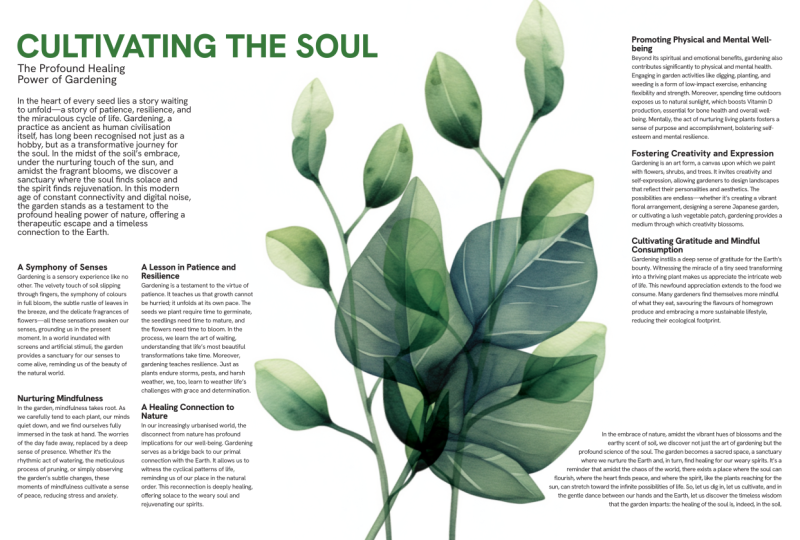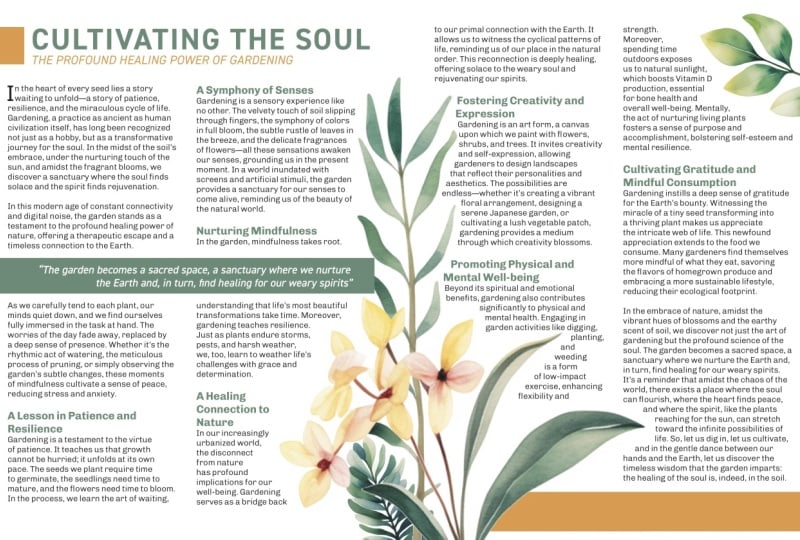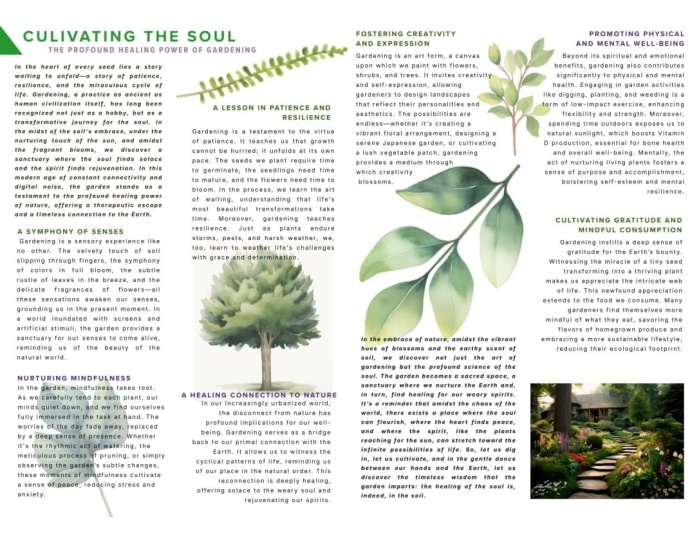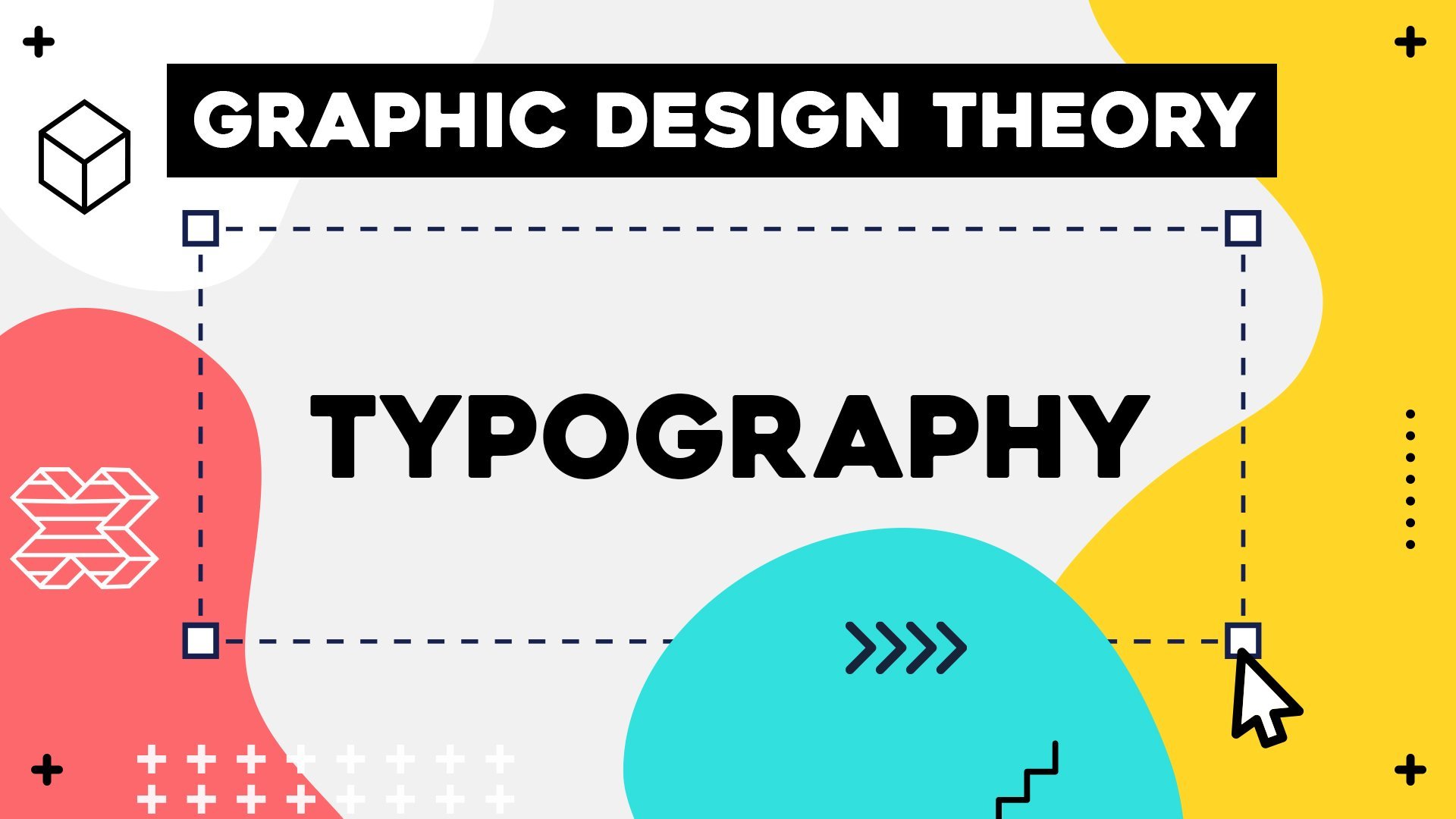
Theorie des Grafikdesigns – Typografie
Einführung
Warum über Typ lernen?
Lesbarkeit
Kalligrafie und Lettering
Schrift vs. Schriftart
Klassifizierung von Schriften
Serif vs. Sans Serif
Typanatomie
Führen, Tracking, Kerning
Auswahl von Schriftarten
Pairing von Schriftarten
Häufige typografische Fehler
Anpassen von Schriftarten
Text für visuelles Interesse
Hierarchie mit Schriftarten
Überlegungen bei der Auswahl der Textfarbe
Textausrichtung
Nützliche Tastatur-Kurzbefehle
Zusätzliche Tastatur-Shortcuts
Schlussbemerkung
Über diesen Kurs
Lass Text in allen deinen Kompositionen professionell aussehen!
In diesem Kurs erkunden wir den Bereich der Schriftarten. Wir lernen die kritischen Prinzipien dazu, wie du sie als bestimmende Figur deines Designs verwenden kannst, um die von dir vermittelte Botschaft zu unterstützen und zu verbessern.
Wer würde von diesem Kurs am meisten profitieren?
Wenn du großartige Typografie auf einem Plakat liebst, wird ein sauberes Leseerlebnis auf einer Website für dich von Anfang bis Ende eine Freude sein.
Wenn du Designer bist, ist das, was du hier beherrschen wirst, ein grundlegendes Element in deiner kreativen Karriere. Wenn du die maßgeblichen Regeln der Typografie verstehst, kannst du den Ton deines Designs meisterhaft festlegen und eine subtile Hierarchie innerhalb der Komposition etablieren, um die Aufmerksamkeit deiner Zuschauer zu kontrollieren.
Warum ich diesen Kurs gemacht habe?
Es gibt so viele Fallen und Fehler, die du machen kannst, von einer visuellen Disharmonie bis zur Störung der Lesbarkeit und Lesbarkeit von Text in deinen Kompositionen. Ich habe dieses Programm erstellt, damit du diese intuitiv vermeiden und Typografie funktionieren lassen kannst.
Am Ende dieses Kurses entwickelst du ein kritisches Auge für die richtige Schriftart und siehst, wie du sie leicht anpassen kannst, um die gute perfekt zu machen – und dieser Unterschied macht einen Designer und seine Arbeit aus.
Was werden wir in diesem Kurs behandeln?
Wir erkunden alle praktischen Aspekte der Typografie, einschließlich:
• Der Prozess der effektiven Schriftart und Paarung
• Schlüsselbegriffe der Typ-Anatomie und die Klassifizierung von Schriftarten
• Der Unterschied zwischen Schriftarten und Schriftarten, Kalligrafie und Lettering
• Textausrichtung, Raster, Text- und Bildpositionierung
• Professionelle Schriftanpassung
• Best Practices für die Erzeugung visuellen Interesses und die Kontrolle der Wahrnehmung
• Häufige Typografie-Fehler und Möglichkeiten, sie zu vermeiden
• Die goldenen Regeln für die Auswahl der Textfarbe
• Nützliche Tastaturkürzel in Adobe-Design-Anwendungen
• Und vieles mehr
Alles in Aktion sehen
Während dieses Kurses analysieren wir verschiedene Designs – von Plakaten, Buchumschlägen, Visitenkarten und Plakaten bis hin zu Websites, mobilen Apps und Banner-Anzeigen. Dies macht das Training nicht nur wirklich Spaß, sondern hilft dir auch, die Begriffe zu verstehen und sich daran zu erinnern, die wir durch diese Beispiele behandeln,
Wir werden auch jede Einstellungsoption sorgfältig durchgehen, um den Typ anzupassen und zu erkunden, wie dies die allgemeine visuelle und Lesbarkeit beeinflussen würde.
Über mich und meine neue Grafikdesign-Theorie-Serie
Diese neue Grafikdesign-Theorie-Reihe (Typografie ist der zweite Teil) ist die Essenz meiner 15-jährigen Tätigkeit als Unterrichter in Grafikdesign und meiner 20-jährigen Tätigkeit als freiberuflicher Grafikdesigner und Illustrator.
1. Einführung: Das Hauptziel der Typografie ist eine effektive Kommunikation. Sie kann jedoch viel mehr bewirken , als nur Eignung und Lesbarkeit von Text zu gewährleisten Gute Typografie kann auch den Ton eines Designs bestimmen, innerhalb einer Komposition eine Hierarchie etablieren und die Aufmerksamkeit der Zuschauer und die Aufmerksamkeit der In diesem Kurs werden wir alle Aspekte der Typografie behandeln, einschließlich Informationen zur Anatomie der Schrift, Textausrichtung, zur Klassifizierung von Schriften, häufigen typografischen Fehlern und Möglichkeiten, sie zu vermeiden, und vieles mehr, um das Training spannend zu gestalten und Ihnen zu helfen, die behandelten Begriffe zu verstehen und sich daran zu erinnern Wir werden verschiedene Designs analysieren von Postern, Buchumschlägen, Visitenkarten und Werbetafeln bis hin zu Websites, mobilen Apps Am Ende dieses Kurses werden Sie Texte nie mehr auf die gleiche Weise betrachten Auch hier werden Sie das Abschneiden von Schauspielernamen auf Filmplakaten beurteilen , Flüsse und Flüsse in Zeitschriften entdecken und die unterhaltsamen Optionen in Restaurantmenüs die Lupe nehmen Das mag zwar Ihre Familie und Freunde nerven, Sie werden sich als Grafikdesigner zusammen mit dem spannenden Klassenprojekt, das Sie hoffentlich am Ende des Kurses abschließen werden, viel sicherer fühlen Grafikdesigner zusammen mit spannenden Klassenprojekt, das Sie hoffentlich am Ende des Kurses abschließen werden, Sie hoffentlich am Ende des Kurses abschließen werden Sie haben auch das Analyse-Arbeitsblatt und das Begriffs-Glossar , mit denen Sie alles, was Sie gelernt haben, in die Praxis umsetzen können Ich hoffe, Sie freuen sich genauso wie ich darauf, loszulegen und in das Meer des Wissens und der schönen Grafikdesign-Beispiele einzutauchen und der schönen Grafikdesign-Beispiele 2. Warum über Type lernen?: Die erste und wahrscheinlich wichtigste Frage ist, warum Sie überhaupt etwas über Typografie lernen sollten? Nun ja, bei den meisten Designs hätte man sie eintippen müssen. Einige von ihnen verlassen sich stark auf Schrift, wie z. B. eine Zeitschriftenseite, eine Broschüre oder ein Poster. Aber andere Designs, bei denen es vielleicht mehr um Illustration oder Fotografie geht, haben vielleicht nur kleinere Textmengen. Aber Schrift ist in der Regel immer noch ein integrales und wichtiges Detail , das offensichtlich dazu beiträgt, die Botschaft zu vermitteln , für die das Design gedacht ist. Denn vergessen Sie nicht, Grafikdesign ist eine Form der visuellen Kommunikation. Und neben Bildern und Bildern ist es die klarste Botschaft, die wir immer mit Text vermitteln können Text ist jedoch auch etwas restriktiver als Bilder, da er auf der Sprache basiert, die wir verwenden, und manchmal sogar auf der Art der Sprache, die der Sprache Selbst wenn Sie Englisch sprechen, verwenden Sie möglicherweise Begriffe, die Ihnen nicht bekannt sind Im Vergleich zu Bildern kann Text also immer etwas restriktiver sein Es kann jedoch in allem, was Sie zu kommunizieren versuchen, viel klarer Auf meinem Bildschirm können Sie Beispiele für alle Arten von Designs sehen . Wir haben hier Buchumschläge, wir haben Poster, Produktverpackungen, Magazine, Webdesigns, Websites, Webbanner, Illustrationen, Logos, UX-Design und sogar Filmcredits und Straßenschilder. Allen gemeinsam ist die Verwendung von Textelementen Und ich versuche nicht, oder ich habe nicht einmal das Gefühl, dass ich Sie davon überzeugen muss , dass es für jeden Designer von entscheidender Bedeutung ist, Text zu beherrschen und damit zu arbeiten für jeden Designer von entscheidender Bedeutung ist, Text Denn genau wie andere Fähigkeiten, wie zum Beispiel der Umgang mit Farben oder das Entwickeln guter Kompositionen, Arbeit mit Text und das Verständnis von Typografie gibt Ihnen die Arbeit mit Text und das Verständnis von Typografie im Grunde Selbstvertrauen, wann immer Sie ein Design erstellen müssen Typografie ist ein großes Thema und hat viel Tiefe. Wir könnten also viele, viele Stunden damit verbringen, all diese Regeln zu behandeln jeden Begriff und jede Definition zu lernen , die Ihnen einfällt Und ich glaube nicht , dass das nützlich wäre. Ich glaube also, dass es bestimmte Begriffe und Definitionen gibt , die Sie kennen müssen, und diese sind sehr nützlich und werden Ihnen wirklich helfen, Ihre Arbeit zu verbessern. Es gibt zwar noch andere , die auch in ganz bestimmten Fällen nützlich sein können oder falls Sie planen, Ihre eigenen Fonds zu gründen oder zu gestalten. Aber mein Ziel beim Diskurs ist Sie auf den neuesten Stand zu bringen, ein sehr solides und selbstbewusstes Niveau dem Sie verstehen, worauf Sie achten müssen, wie Sie Ihre Fonds auswählen sollten, was sind die Überlegungen, wie Sie sie paaren sollten. Und ich glaube, dass es am nützlichsten sein wird, sich wirklich auf diese entscheidenden Fähigkeiten zu konzentrieren und an realen Beispielen zu üben und an realen Beispielen . Dies ist also keineswegs ein vollständiger Leitfaden, der jeden einzelnen Begriff und jede einzelne Definition abdeckt , sondern eher eine komprimierte und vereinfachte Wissensquelle , auf die Sie sich verlassen können , wenn Sie etwas erstellen müssen , das Textelemente beinhaltet Nun, da wir uns darüber im Klaren sind, warum es nützlich ist, etwas über Typografie zu lernen, werden wir in unserer nächsten Lektion mit einem sehr wichtigen Unterschied zwischen Lesbarkeit und Lesbarkeit beginnen in unserer nächsten Lektion mit einem sehr wichtigen Unterschied zwischen Lesbarkeit und Lesbarkeit 3. Lesbarkeit: Sie haben wahrscheinlich von Lesbarkeit oder vielleicht von beidem gehört oder Lesbarkeit oder vielleicht von beidem Und es ist ziemlich schwierig , diese beiden Begriffe oder Ziele zu unterscheiden diese beiden Begriffe oder Ziele , auf die Sie als Designer wirklich achten müssen Lesbarkeit ist wahrscheinlich diejenige, von der Sie am meisten gehört haben und die wahrscheinlich Sinn macht Es bedeutet im Grunde, ob Sie etwas lesen können oder nicht. Es geht also eher darum, ob Sie physisch in der Lage sind , einen Text auf einem Design zu verstehen. Nun, es gibt normalerweise einen deutlichen Unterschied zwischen dem Umgang mit Fließtexten , wie Sie es in Büchern und Zeitschriften tun würden, und dem Umgang mit den wichtigsten Textelementen Sie könnten also den Einführungsabsatz oder den Eintragsabsatz verwenden, wobei der Text manchmal größer Und dann würden Sie den Rest der Kopie in kleinerem Text schreiben Aber dann haben Sie auch Überschriften, Titel oder Kapiteltitel, die normalerweise viel größer und unterschiedlich formatiert sind und unterschiedlich formatiert Aus Gründen der Übersichtlichkeit müssen all diese Elemente lesbar sein, sodass der Betrachter sie lesen kann Aber wie Sie sie präsentieren, hängt wirklich von ihrer Rolle , die sie innerhalb des Designs spielen Während der Haupttext ein längerer Text ist , der leicht lesbar sein muss, könnten Titel immer etwas verspielter sein, da sie kürzer und größer sind, sodass mehr Platz zum Herumspielen bleibt. Hier auf der linken Seite haben wir zum Beispiel eine große Zahl, die das Kapitel markiert das vom eigentlichen Kapiteltitel überlagert wird Wirkt sich das auf die Eignung aus? Ich würde sagen, das ist nicht so, weil wir einen deutlichen Kontrast zwischen den Farben haben Wir haben also Schwarz und Rot übereinander, was sehr leicht zu unterscheiden ist. Außerdem haben wir einen enormen Kontrast in der Größe und sogar in der verwendeten Schriftart. Der schwarze Text verwendet also eine normale sensorische Schrift wie Helvetica, wir haben für die Zahlen im Hintergrund eine kondensierte Boulder-Schrift verwendet , um die Eignung sicherzustellen Auf der rechten Seite haben wir die gängigsten und komfortabelsten Farben verwendet: weißer Hintergrund und schwarzer weißer Hintergrund Wenn Sie jemals den entgegengesetzten weißen Text auf schwarzem Hintergrund oder hellen Text auf dunklerem Hintergrund verwenden , würden wir das als umgekehrten Text bezeichnen Und es kann immer noch funktionieren. Es sind jedoch dieselben Farben, sie sind nur invertiert. Das Design wird immer noch etwas an Lesbarkeit leiden, daher würde ich nicht empfehlen, es für längere Texte zu verwenden, wie für ein Buch oder eine Zeitschrift Aber für ein Poster wie dieses könnte es ganz gut funktionieren Und es kann leicht auffallen und auch die Stimmung oder den Ton des Designs bestimmen. Warum sollte dieses Poster einen schwarzen Hintergrund verwenden? Nun, aus irgendeinem Grund wird Jazz, wann immer wir an Jazz denken, normalerweise nachts gespielt. Es hat also bereits diese Konnotation in unserem Kopf, und vor allem, weil der Text es auch als nächtliche Unterhaltung bezeichnet , macht es wirklich Sinn Aber vergessen Sie auch nicht, dass Sie auf dem Klavier, dem am häufigsten verwendeten Instrument für Jazz, schwarze und weiße Tasten haben, die natürlich mit weißem Hintergrund und schwarzem Text darüber dargestellt werden könnten weißem Hintergrund und schwarzem Text darüber Die meisten Klaviere, die eigentlichen Instrumente, die die Jazzmusiker verwenden, sind jedoch die eigentlichen Instrumente, die schwarz Ein schwarzer Hintergrund und viel negativer Leerraum sorgen also für das natürliche Verhältnis von Instrument und Tastatur All das zu verstehen, hilft uns erst, die Komposition und die Farbauswahl auf diesem Poster zu schätzen die Farbauswahl auf diesem Poster Jetzt, wo wir anfangen zu verstehen wie man mit Lesbarkeit arbeitet, finden Sie hier einige Beispiele, die das Konzept , Text lesbar zu machen, in Frage stellen Wir haben zum Beispiel dieses leere Poster, wo wir immer noch den Titel lesen können, und all diese Untertitel sind sekundäre Informationen, aber das ist für den Betrachter eine Herausforderung Wir müssen ein bisschen härter arbeiten , um alles zusammenzustellen, und wir müssen fast die Seite umblättern , um die Dinge richtig lesen zu können. Diese Zusammensetzung oder dieses Layout wirkt sich also definitiv auf die Lesbarkeit Es reduziert sie, aber da nicht viel Text durchgehen muss, wird es nicht nervig sein Stattdessen wird es eher eine spielerische und unterhaltsame Übung sein , die Informationen auf dem Poster oder Flyer durchzugehen . Es kann auch Beispiele und Gründe geben, warum ein Designer entscheidet, mit Zeichen oder Schriften wie hier herumzuspielen. Zum Beispiel gibt es viele Möglichkeiten , wie der Betrachter herausgefordert wird , lesen zu können. Der Haupttext ist nicht nur in mehrere Zeilen aufgeteilt, sondern es gibt auch keine klare Ausrichtung, sodass wir sowohl links als auch rechts einen zackigen Rand haben Aber was noch wichtiger ist, wir haben sogar jedes der Charaktere aufgeteilt oder in kleine Teile aufgeteilt All dies wirkt sich also negativ auf die Lesbarkeit aus. Es gibt jedoch auch Dinge , die dies unterstützen. Zuallererst die Größe des Textes, der hier verwendet wird, aber auch der Kontrast zum Hintergrund. Schwarz ist also offensichtlich die Farbe mit dem höchsten Kontrast, die in diesem Design verwendet wird. Das hebt sich wirklich vom Hintergrund ab, obwohl es wieder einige verwirrende, farbenfrohe Formen dahinter gibt . Und das geht zurück zu der wichtigsten Lektion lernen muss, wenn man einmal verstanden welche Regeln in diesem Fall gelten, dass man die Lesbarkeit sicherstellen muss. Der nächste Schritt besteht immer darin, Der nächste Schritt besteht immer diese Grenzen zu also die Regeln verstehen, werden Sie das Selbstvertrauen haben, die Grenzen zu überschreiten und Ihre Zuschauer wirklich herauszufordern, ohne dass Ihre Designs nervig oder verwirrend Das heißt nicht , dass du immer solche Designs machen musst. Auch hier haben wir eine sehr schlechte Lesbarkeit bei diesem Text oder bei diesem, bei dem bestimmte Zeichen wirklich ausgestreckt sind bestimmte Zeichen wirklich ausgestreckt Ganz zu schweigen von der Art der Illustrationen , bei denen der Text nicht wirklich gelesen werden soll Es wird eher als grafisches Element verwendet , um ein Porträt nachzubilden oder eine bestimmte Botschaft zu vermitteln Aber neben der Verwendung von Text auf diese unkonventionellere Weise möchten Sie in den meisten Fällen auch wirklich die Lesbarkeit Sie möchten also eine sehr gute Lesbarkeit haben, wie beim Design der Benutzeroberfläche Die Botschaft muss sehr klar sein, wo Benutzer bestimmte Funktionen finden können Und der Text muss auch eine gute Hierarchie aufweisen, egal ob es sich um schwarzen Text auf einem Hintergrund oder um umgekehrten Text Wie wir bereits gesehen haben, müssen Sie sich als Designer die Lesbarkeit als einen Schieberegler vorstellen , den Sie für bestimmte Elemente wie die Namen einer Pizza anpassen können bestimmte Elemente wie die Namen einer In diesem Fall kann die Lesbarkeit etwas verringert werden, um den Namen diesen Geschmack und Stil zu verleihen, während die Zutaten und der zusätzliche Text unten und vor allem Handlungsaufforderungen Elementen wie Schaltflächen sollte eine wesentlich bessere Lesbarkeit erreicht werden, hauptsächlich in diesem Fall durch die Verwendung von Schriften, die generell viel einfacher zu lesen sind 4. Lesbarkeit: Es ist also an der Zeit, über Lesbarkeit zu sprechen. Das ist die andere Art, darüber nachzudenken wie Sie Schrift in Ihren Designs präsentieren sollten Und der Hauptunterschied im Vergleich zur Lesbarkeit besteht darin, ob Ihr Betrachter oder Leser Ihre Designs oder die Textelemente in Ihren Designs lesen möchte Designs oder die Textelemente in Ihren Designs lesen die Textelemente in Es geht also nicht darum, es lesen zu können , was Lesbarkeit war Es geht darum, ob sie es lesen wollen oder nicht. Es geht also eher um ihren Wunsch, ob sie dein Exemplar lesen wollen oder nicht, oder wie viel Spaß oder Freude sie beim Lesen haben. Wie können Sie die Lesbarkeit verbessern? Sie können sich Lesbarkeit als die Benutzerfreundlichkeit Ihrer Schrift oder die Ergonomie Ihrer Typografie vorstellen Benutzerfreundlichkeit Ihrer Schrift oder die Ergonomie Ihrer Typografie oder die Ergonomie Und der effektivste Weg, die Lesbarkeit Ihrer Designs zu verbessern, insbesondere wenn Sie viel Text haben, besteht darin, so viele Einstiegspunkte wie möglich zu haben Wir werden später darüber sprechen, aber im Wesentlichen geht es darum, diese klaren Punkte zu haben , an denen Leser auf dieser Seite mit dem Lesen beginnen können. Wir haben viele Bereiche, in denen sie mit dem Lesen beginnen können. Wir haben hier auch eine klare Überschrift oder einen klaren Titel. Wir haben dort auch einen weiteren kleinen Abschnitt. Wir haben auch diese riesigen Zahlen uns helfen, durch den Text zu springen, sodass wir der ursprünglich beabsichtigten Richtung oder Route der Kopie klar folgen oder Route der Kopie Und all diese Hinweise und Unterteilungen in der Kopie helfen uns die Informationen zu verdauen und sie ohne großen Aufwand durchzugehen Und die Tatsache, dass die Reihenfolge des Textes hier ein bisschen uneinheitlich ist, sodass er zwischen den Seiten hin- und herspringt ist kein großes Problem, weil es , ist kein großes Problem, weil es tatsächlich hilft, das Auge des Betrachters von links nach rechts und dann wieder zurück zu bewegen Auge des Betrachters von links nach rechts und dann wieder zurück zu Es bietet also fast ein bisschen Übung oder Herausforderung, ohne wieder nervig zu sein. Und das ist auch eine gute Balance mit der man als Designer spielen muss. Sie möchten also nicht, dass Ihr Design zu langweilig ist und viele Texte an einem Ort hat. Sie möchten aber auch nicht, dass Ihre Designs zu schwer zu lesen sind. Also hier ist ein interessantes Beispiel. Wir haben viele Texte in diesem Block in der Mitte. Das ist unser Haupttext, aber wir haben einen Einstiegspunkt , der eine Drop Cap ist. Und wir haben auch einige Umfragecodes , die den Text auflockern. Und dann der Haupttitel und der Intro-Absatz hier in der Mitte Da es sich um eine Zeitung handelt, können wir mit einer Menge Exemplaren rechnen , die auf einer einzigen Seite platziert werden müssen Und obwohl wir diesen großen Textblock mit sechs Spalten haben , macht er trotzdem Spaß, dank der Abbildung, die durch den Text geteilt ist durch den Text geteilt und oben und unten erscheint. Und auch durch diese negativen Leerzeichen oder Pausen im Design Das wiederum trägt einfach dazu bei, ein bisschen Verspieltheit zu erzeugen und dem Leser etwas Luft zum Atmen zu lassen etwas Luft zum Atmen Aber hier gibt es noch ein weiteres interessantes Detail. Der Titel des Magazins ist tatsächlich fast vollständig, oder zumindest die Hälfte davon, hinter der Abbildung versteckt. Nun, das ist auch etwas, das Sie häufig auf Titelseiten von Zeitschriften sehen. Und es hängt davon ab, dass der Leser mit der Zeitung vertraut ist und den Titel wiedererkennen würde , auch wenn er nicht vollständig ist. Auch hier blockiert das tatsächlich die Lesbarkeit. Wir sind einfach physisch nicht in der Lage, diesen Teil des Textes zu lesen Aber was die Lesbarkeit angeht, stellt dies eine unterhaltsame Herausforderung dar und kann wiederum die Aufmerksamkeit des Lesers da es hier eine Lücke hinterlässt, die unser Verstand über diesen Titel ausfüllen muss Was die Lesbarkeit angeht, ist es wirklich schwach, was die Lesbarkeit angeht Es ist eigentlich ziemlich gut , weil es das Interesse des Lesers weckt Und zum Schluss werde ich Ihnen drei Beispiele zeigen, bei denen sowohl die Lesbarkeit als auch die Lesbarkeit schlecht sind, und ich muss Sie warnen, es könnte Ihre Augen verletzen Hier sind diese Beispiele. Erstens haben wir Beschilderungen, die für Londoner Busse verwendet werden. Ich glaube nicht, dass dieses Schild mehr draußen ist. Ich bin mir sicher, dass es mit dem Transport nach London repariert wurde. Aber als es fotografiert wurde, es eindeutig einige Probleme, die sich sowohl auf die Lesbarkeit als auch auf die Lesbarkeit auswirkten Das größte Problem ist das schlechte Tracking oder Kerning, das dazu führte, dass sich diese Zeichen an bestimmten Stellen zu nahe kamen einige davon fast zu Ligaturen Ungewollt handelt es sich bei Ligaturen um Schriftpaare bei denen es sich normalerweise um einzelne Zeichen innerhalb einer Schrift handelt Aber wir haben auch eine wirklich schlechte Trennung wichtiger Details, wie zum Beispiel die zweigeteilte Haltestelle M oder die zweigeteilte London Bridge Selbst bei einem kleinen Maß oder einer geringen Linienbreite wie hier sollten sie immer noch in derselben Linie zusammengehalten werden. Was jetzt noch schlimmer ist, ist, dass ich glaube hier sogar ein Grammatikfehler vorliegt Ich denke also, dass dieser Apostroph ein Fehler ist, weil er Wurzeln 43,141 bedeuten sollte, aber derzeit würde es bedeuten, dass diese Zahlen Grammatikfehler oder Tippfehler wie diese würden hauptsächlich die Lesbarkeit beeinträchtigen, weil sie Verwirrung stiften und der Leser einige Informationen tatsächlich falsch interpretieren könnte , falls ein Zeichen, das darauf hinweist , von einem Ort zum anderen zu gelangen, ein ernstes Ort zum anderen zu Die anderen beiden Beispiele, die wir hier haben, sind in Bezug auf Lesbarkeit und Lesbarkeit gleichermaßen schlecht Wir haben sehr schlechte Designentscheidungen in Bezug darauf, welche Farben übereinander verwendet werden, welche Art von Schriften für bestimmte Informationen verwendet werden, die Unterschneidung, das Tracking und die Ausrichtung von Dingen, die unnötige Vielfalt an Schriften, die in einem Design gestapelt Und ich könnte weitermachen, ich bin mir sicher, dass Sie all das sehen können. Und ich glaube, damit sich jeder verbessern kann, ist es genauso wichtig, sich diese schlechten Beispiele anzusehen und sie zu analysieren , wie Zeit zu investieren und sich gute Beispiele anzusehen , die wir zuvor in diesem Video gesehen haben. Nun, da Sie sich Ihrer Hauptziele, der Verbesserung der Lesbarkeit und Lesbarkeit, bewusst sind , werden wir als Nächstes ein wenig über die grundlegenden Begriffe der Typografie sprechen die grundlegenden Begriffe der Typografie 5. Kalligrafie und Lettering: Sie haben wahrscheinlich von Kalligrafie oder Handlettering gehört, und das sind völlig andere Fähigkeiten als das Setzen von Schrift. Als Grafikdesigner arbeitest du hauptsächlich mit Das sind also Telefone , die du für deine Designs verwenden kannst und alle Charaktere sind schon da. Sie müssen nur anfangen, sie einzugeben und natürlich an der Komposition zu arbeiten. Vergleich dazu, wenn Sie gebeten werden, Kalligrafie oder Handlettering zu machen, das ist eher eine Kunstform, die der Illustration ähnelt bei der jeder Charakter einzeln in einem bestimmten Stil gezeichnet werden muss . Es ist schwierig, diese beiden Begriffe klar zu unterscheiden Ich würde jedoch sagen, dass Kalligrafie eher ein traditioneller Ansatz ist, und Sie können hier einige Beispiele in verschiedenen Sprachen sehen Sie würden sie in Enzyklopädien und alten Lexika finden. Traditionell wurde diese Art des Schreibens für alles verwendet, auch für Titel, Drop-Caps und sogar den Heutzutage wird es in der modernen Kalligraphie jedoch normalerweise für einzelne Wörter oder Phrasen verwendet Und der Haupttext wird sehr selten in diesem Stil geschrieben. Selbst einzelne Charaktere können sehr komplex und ansprechend aussehen, sodass sie beispielsweise problemlos als Gestaltungselement auf einer Zeitschriftenseite oder als wirklich hervorstechendes Dropcap verwendet beispielsweise problemlos als Gestaltungselement auf einer Zeitschriftenseite werden können, auf der anderen Seite Handlettering , das heutzutage entweder traditionell oder digital sein kann heutzutage entweder traditionell oder digital Offensichtlich ist es auf dem iPad sehr einfach, zum Beispiel den Apple Pencil zu verwenden und diese Art von Kompositionen zu erstellen Das unterscheidet sich meistens von der Kalligrafie dadurch , dass der Text hier eher als Komposition verwendet wird, sodass jedes der Wörter ein größeres Layout bildet und es entsteht ein hübsches Abzeichen, meistens in Form ein größeres Layout bildet und es entsteht ein hübsches Abzeichen, meistens in Es kann sich entweder um einen Kreis, ein Quadrat oder um beliebige organische Formen handeln Und es ist sehr üblich, auch einige florale, dekorative Elemente oder illustrative Details mit dem Schriftzug zu kombinieren Wie ich bereits sagte, sind Kalligrafie und Handlettering keine Fähigkeit, die Sie als Grafikdesigner beherrschen müssen Dies ist eine völlig eigenständige Kunstform und ähnelt eher der Illustration, wie ich bereits erwähnt habe Wenn Sie jedoch daran interessiert sind, solche Arbeiten zu produzieren, werden die Prinzipien und Theorien, die wir in diesem Kurs lernen, für Sie äußerst nützlich sein. 6. Schrift vs. Schrift: Sie kennen den Begriff Schrift wahrscheinlich schon. Und die meisten Grafikdesigner verwenden dies häufig und beziehen sich nur darauf, welche Schriftart für ein bestimmtes Design verwendet werden soll. Oder welche Schriften sich gut miteinander kombinieren lassen. Schrift ist jedoch ein weiterer Begriff , mit dem Sie vertraut sein sollten Und tatsächlich kann man argumentieren , dass die richtige Art, sich auf die meisten Schriften zu beziehen, darin besteht, sie Schriften zu nennen Helvetica ist zum Beispiel ein Schriftbild. Futura oder Gotham sind auch zwei andere Gesichter. Die Schriftarten sind die verschiedenen Variationen von ihnen. Normalerweise nennen wir eine Schrift eine Schriftfamilie Helvetica. Das Schriftbild hätte zum Beispiel eine ultraleichte Schriftversion oder die römische Schrift Helvetica oder die schwarze Schrift eine ultraleichte Schriftversion oder die römische Schrift Helvetica oder die schwarze Schrift Helvetica. Und all diese Variationen oder Schriften bilden die Schriftfamilie oder das Schriftbild Helvetica Niemand wird Sie korrigieren , wenn Sie sagen, dass Helvetica Aber wenn Sie genauer sein wollen, versuchen Sie, sie als Schriftbild zu bezeichnen Aber natürlich kann man immer noch sagen, dass ich zum Beispiel die Helvetica-Boardschrift für den Titel in einem Design verwendet habe In einer anderen Lektion werden wir mehr darüber sprechen, was in einer Schrift enthalten ist oder was normalerweise auch der Inhalt einer Welche Schriftarten sind empfehlenswert, um sich an die Arbeit zu gewöhnen , und welche, die Ihnen wirklich gute Dienste leisten werden, vor allem dank der Vielfalt der darin enthaltenen Schriftarten 7. Klassifizierung von Schriften: Sie haben wahrscheinlich schon von den Fonds Serif und San Serif Typefaces gehört , und das ist eine Möglichkeit, Aber es steckt tatsächlich noch viel mehr dahinter. Und es ist auch wichtig zu wissen, wann welche Schriftklasse verwendet werden muss. Deshalb werden wir in diesem Gespräch mit Ihnen die wichtigsten Informationen zu diesem Thema behandeln . Zuallererst, was sind Serifen? Dies sind die kleinen Details oder Verzierungen, die dazu beitragen, Buchstaben auf Serifenschriften unverwechselbarer zu machen, während Sonne eigentlich ohne bedeutet während In diesem Fall, also ohne Serifen, hätten diese Arten von Schriften keine Verzierungen Sie wären viel einfacher und minimalistischer . Serifenschrift, manchmal auch als Roman bezeichnet. Und das liegt hauptsächlich daran, dass sie auf dem Gravierstil der römischen Schrift basierte , während Sunserif manchmal als grotesk bezeichnet wird Das ist jedoch nur eine bestimmte Art von Sanserif. Es ist wahrscheinlich besser , diesen Begriff nicht als allgemeine Klassifikation zu verwenden , bevor Sie mehr über den Unterschied zwischen Sanserif - und Serifenschriften erfahren zwischen Sanserif Hier finden Sie einige Hintergrundinformationen zu den Schriften aus der Geschichte oder Entwicklung Und das ist ein großes Thema und ich möchte nicht alles behandeln Aber diese Infografik fasst die Dinge wirklich gut zusammen, denn sie zeigt sehr deutlich die vier wichtigsten Klassen oder Kategorien für Schriften oder Schriften Zunächst haben wir also ein Skript, in dem Sie schwarze Buchstaben am häufigsten erkennen würden erkennen Das sind also die wirklich alten, traditionellen Buchstaben, die zu der Zeit erfunden wurden, als der erste Druck begann. Es ist also ungefähr zu der Zeit Johannes Gutenberg die bewegliche Schrift mit der Druckmaschine erfand mit der Druckmaschine Und diese Schriftbilder ahmten immer Handbeschriftungen nach Sie haben sich auch im Laufe der Zeit weiterentwickelt, sodass sie mit dem neuen Casual-Format und später mit der formellen Version etwas einfacher zu lesen waren neuen Casual-Format und später mit der formellen Version etwas einfacher zu Aber wie Sie sehen können, waren sie die ersten, die wir als Schriften in Betracht ziehen würden Und dann, nicht viel später, erschienen die ersten Serifenschriften oder Schriften Das ist also die zweite Farbe, die wir hier haben, und es gibt viele Kategorien für sie, aber die erste, die wir um das frühe 16. Jahrhundert herum in Betracht ziehen würden , war die Kategorie des alten Stils Adobe-Kleidung ist ein Beispiel dafür. Aber natürlich gibt es viele Variationen und es hat sich im Laufe der Zeit weiterentwickelt und verändert Aber selbst wenn Sie sich diesen Text hier ansehen, können Sie immer noch das Erbe und die klassische Atmosphäre erkennen , die auch in diesem neuen digitalen Format erhalten geblieben sind . also zu unserer Infografik zurückkehren, können wir sehen, dass Serve-Fonds tatsächlich seit über 500 Jahren existierten, aber Sunsifunds gab es erst um 1.800. Dies ist erneut ein wichtiger Übergang in der Geschichte der Schriftgesichter und der bemerkenswerteste und wichtigste, den es zu erwähnen gilt , ist Caslon, hier können wir William Caslon sehen. An vierter Stelle stand die Einführung des Sunserif-Drucktyps. Dies war eine revolutionäre Veränderung oder ein revolutionärer Schritt in der Druckgrafik, , wirklich beeinflusst Art und Weise, wie wir bis heute mit Schrift arbeiten Aber jetzt wissen Sie , dass die Schriftzeichen von Sunserif zwar modern aussehen, aber inzwischen mehr als 200 Jahre alt sind Und sie haben sich im Laufe der Zeit weiterentwickelt und verändert, genau wie Gesichter vom Typ Sunserif Es gibt also verschiedene Kategorien wie grotesk, humanistisch, geometrisch, quadratisch und so weiter Schließlich tauchte die letzte Kategorie, die wir als dekorative Schriften betrachten würden , zu Beginn des 20. Jahrhunderts auf Und davon finden Sie auf kostenlosen Schriftseiten wie Dafont eine Fülle davon Aber selbst bei Adobe-Schriften würden mehrere Tags Sie zu solchen dekorativen Schriften führen , wie zum Beispiel lustige oder flippige Nun, diese sind in der Regel von allen Klassen am wenigsten lesbar Sie können sich jedoch hervorragend dazu eignen, einen ganz bestimmten Tonfall oder ein ganz bestimmtes Thema für Ihren Text einzufangen einen ganz bestimmten Tonfall oder ein ganz bestimmtes Thema für Ihren Text Und natürlich werden diese hauptsächlich für Titel und Überschriften verwendet und nicht für den Haupttext oder längere Textmengen. 8. Serif vs. Sans Serif: wir nun ein kurzes Verständnis davon haben, wie sich diese Schriftklassen entwickeln, können wir uns auf den Unterschied zwischen Serif und Sunseriffunds konzentrieren zwischen Serif Denn als Grafikdesigner sind dies die wichtigsten, mit denen Sie Und Sie sollten die Vor- und Nachteile der Verwendung eines Produkts gegenüber dem anderen kennen . Als allgemeine Richtlinie würden die meisten Kreativen empfehlen, in gedruckter Form mit Serifen- oder Römischen Schriften zu arbeiten und Sunserif im Internet oder in einem beliebigen digitalen Format zu verwenden Das ist eine Art Verallgemeinerung. Es stimmt jedoch, dass die Serifen-Attribute oder -Details zur Lesbarkeit beitragen, da sie zunächst eine allgemeine Orientierung oder horizontale Richtung für das Lesen geben eine allgemeine Orientierung oder horizontale Richtung All diese kleinen Details dienen dazu, Sie durch das Lesen des Textes zu führen Aber noch wichtiger ist, dass sie auch Charaktere zusammenfügen und bessere Einheiten für Wörter bilden. Auch hier ist das bei längeren Textmengen sehr hilfreich, da die Leerzeichen zwischen den Wörtern dann deutlicher werden. Und wie gesagt, Wörter werden zu besseren Einheiten zusammengefügt. Warum sollten wir also jemals Sunsif verwenden, wenn es einfacher ist, Serif-Schriften zu lesen Nun, einer der Hauptgründe warum Sie im digitalen Design Sunserif statt Serif verwenden würden , ist die Verpixelung der Serifendetails , warum Sie im digitalen Design Sunserif statt Serif verwenden würden, ist die Verpixelung der Serifendetails. Sie haben bereits kleinen Text, sagen wir für Ihren Haupttext , und er ist auf einer Website, auf diesem kleinen Text würden die noch kleineren Serifen definitiv anfangen die noch kleineren sagen wir für Ihren Haupttext , und er ist auf einer Website, auf diesem kleinen Text würden die noch kleineren Serifen definitiv anfangen zu pixeln. Und das ist nicht wirklich ideal, wenn Sie Sunserif verwenden möchten, insbesondere für kleinere Texte insbesondere für kleinere Texte, wenn es um Websites und Anwendungen, Benutzeroberflächen usw. geht , Benutzeroberflächen usw. Einigen Studien zufolge verwenden rund 70% des Textes auf dem B Sunserif-Schriften Das heißt jetzt nicht, dass Sie Sunserif nicht in gedruckter Form oder Serif im digitalen Format verwenden können in gedruckter Form oder Serif im digitalen Format Dies sind eher allgemeine Richtlinien und Aber solange Sie die Gründe dafür verstehen, können Sie sich in bestimmten Fällen davon lösen Und natürlich können Sie diese beiden auch miteinander kombinieren, sodass Sie sich nicht auf eine Klasse in einem bestimmten Design beschränken müssen auf eine Klasse in einem bestimmten Design Sie können Ihren Introtext und Ihren Titel oder Ihre Überschrift in Sanserif haben , aber Sie können den Haupttext in Serifenschrift haben Ein weiteres Beispiel für die Kombination von drei verschiedenen Kategorien Wir haben die Überschrift in einem komprimierten Sanserif-Text gesetzt. Wir haben diese großen Zahlen, und der Haupttitel ist eher ein dekorativer Fonds Und dann haben wir den Haupttext oder die längere Textmenge und sogar diesen Aufruf hier in Serifenschrift oder die längere Textmenge und sogar diesen Aufruf hier in Serifenschrift Generell gilt: Wann immer Sie Seri-Fonds verwenden, hilft es, Ihr Design etwas moderner, frischer und einfacher zu gestalten Im Vergleich zur Verwendung von Serif-Fonds würden Sie Ihren Designs ein etwas traditionelleres klassisches Flair verleihen Und hier ist ein weiteres Beispiel, dem nur Seri-Fonds auf einem Buchcover verwendet Beides für dieses grafische Design hier in der Mitte, aber der gesamte Rest des Textes ist in Serif geschrieben Die Merkmale oder Unterschiede zwischen den beiden Fondsklassen sind beispielsweise auf dem Google-Logo deutlich sichtbar beispielsweise auf dem Google-Logo Als es auf die Verwendung von Sun Serif gegenüber der ursprünglichen Seri-Schrift umgestellt wurde , hatte dies bereits einen großen Unterschied in der Wahrnehmung der Marke und der Suchmaschine selbst bewirkt Es ist interessant zu sehen, wie viel Unterschied es macht, ob Sie die eine oder die andere Textklasse verwenden Ich wollte aber auch nur darauf hinweisen, dass sie beim Google-Logo ein besonderes Merkmal beibehalten haben , nämlich die Neigung oder Drehung auf dem E, was es wiederum ein bisschen einzigartiger macht Aber auch weniger offensichtlich ist , dass sie die Farben geändert haben Das wohl markanteste ist das Grün. Wie es heller wurde, aber alle anderen Farben haben sich nur geringfügig verändert. Aber zurück zu den Unterschieden oder Vor- und Nachteilen zwischen diesen beiden Hauptklassen von Schrifttypen: Es ist auch erwähnenswert, dass Serifenschriften normalerweise besser funktionieren , wenn es darum geht, Dinge kursiv zu setzen Dies ist etwas, das Sie hier deutlich demonstriert sehen können deutlich demonstriert sehen Kursiv oder Kursiv wird manchmal auch als Schrägschrift bezeichnet Dabei handelt es sich um leicht schräge Zeichen, während Sunserif-Schriften dazu neigen, kontrastarme Schrägzeichen zu haben, was bedeutet, dass sie sich nicht wesentlich von den normalen Buchstaben unterscheiden . hätte viel mehr Kontrast, wenn es um Kursivschrift hätte viel mehr Kontrast, wenn es um Serifenschriften geht Sie können also sehen, dass dieser Text hier ganz anders aussieht und sich vom regulären Zeichensatz abhebt Dies ist wiederum ein großer Vorteil wenn es um Bücher geht, bei denen Kursivschrift oder Schrägschrift häufig Kursivschrift oder Schrägschrift verwendet wird, um bestimmte Dinge hervorzuheben Nehmen wir an, jemand spricht oder auf etwas wird Bezug genommen, kann in diesem Format eingestellt werden Wenn Sie mit serifenlosen Schriften arbeiten, müssten Sie sich mehr auf die unterschiedlichen Strichstärken verlassen Sie können also helle, fett oder extrem fett gedruckte Versionen verwenden oder extrem fett gedruckte Versionen um bestimmte Teile des Textes hervorzuheben Hier ist ein weiteres interessantes Beispiel , das zeigt, dass es bei der Verwendung von Serifenschrift im Vergleich zu San Serif immer einfacher ist, Zeichen zu unterscheiden , da das O und das C für diesen speziellen Typ unterscheiden sind, wenn Sie nur den oberen Teil des Textes betrachten Während die Serif auf dem C steht, verrät dieses kleine zusätzliche Detail immer, was Sie gerade sehen, selbst wenn Sie nur selbst wenn Sie Das ist also offensichtlich ein Vorteil und hilft wiederum, die Charaktere zu unterscheiden Hinzufügen von mehr Details im Grafikdesign bedeutet jedoch , dass die Dinge komplexer werden. Und das ist der Grund, warum Menschen, die sich entspannen, normalerweise als ungezwungener und freundlicher angesehen werden normalerweise als ungezwungener und freundlicher angesehen Und tatsächlich bevorzugen oder finden Kinder es viel einfacher sonnenverwöhnte Texte zu lesen. Es gibt also viele Überlegungen, Vor- und Nachteile. Und ich möchte Sie nicht dazu ermutigen, einfach eine Klasse von Schriftbildern der anderen vorzuziehen. Es geht darum, sich mit den Eigenschaften vertraut zu machen. Und sobald Sie anfangen, mit ihnen zu arbeiten, werden Sie eine Intuition dafür entwickeln wann eine bestimmte Klasse besser ist als eine andere Und wenn Grafikdesign neu für dich und du immer noch Schwierigkeiten hast zu unterscheiden, was ein Gesicht vom Typ Serif oder Sunsif ist, dann würde ich empfehlen, dieses Spiel ein bisschen zu spielen Ich habe den Serif dort gedreht, wo du dein Level einstellen kannst. Und sagen wir einfach, wir sind momentan mittelgewichtig, also werde ich mich einfach dafür entscheiden Wir werden zwei Charaktere bekommen und du musst immer die Serifenfiguren erschießen. Jetzt haben wir vier davon, also müssen wir es einfach noch einmal machen Und wir bekommen immer mehr. Und dann müssen wir das so schnell wie möglich durchstehen. Und wir können sehen, dass wir eine bestimmte Anzahl von Fehlern zulassen, in diesem Fall sechs. Und bis jetzt haben wir so viele Punkte und wir haben 14 richtige Serifenschriften gefunden Ich kann diese nur empfehlen, damit herumzuspielen. Aber es gibt auch eine andere gute, tippe War.com, wo du auch hier in der Lage sein musst, zu erkennen, welche Art von Gesicht du betrachtest Das wird dir helfen , dich mit den am häufigsten verwendeten Schrifttypen vertraut zu machen. Es ist auch eine gute Praxis, sich daran zu erinnern, ob eine Schrift Serifen hat oder nicht In diesem Fall sagen wir Times New Roman. Dann machen wir weiter. Wenn wir jetzt Times New Roman wiedersehen, werden Sie immer sehen, ob Sie Recht haben oder nicht. Auf der linken Seite können Sie die richtige Antwort auf die vorherige Frage finden. Jetzt schauen wir uns, glaube ich, Helvetica Dieser ist optimal, dieser ist Dido, und wir haben eine und wir haben Lass uns einfach versuchen, so weiterzumachen, Dido nochmal, und dieser hier ist Und ich werde damit aufhören, weil ich irgendwann einen Fehler machen werde Denken Sie daran, dass auch die Typografie ein großes Thema ist und es eine Menge Geschichte und Regeln Auch wenn Sie sich im Moment von all den verschiedenen Dingen, die wir behandelt haben, etwas eingeschüchtert fühlen von all den verschiedenen Dingen , denken Sie daran, dass alles davon abhängt, wie viel Spaß Sie daran haben und Schriftgesichter als Ihre Freunde betrachten Sobald Sie sie kennenlernen und wissen, wie man mit ihnen arbeitet, wird es viel mehr Spaß machen und Sie werden Spaß am Gestalten haben . 9. Typanatomie: Wenn es um Begriffe und Definitionen geht, kann ist die Anatomie des Typs das Schrecklichste, dem man begegnen Es gibt so viele Namen für bestimmte Merkmale in Zeichen oder Buchstaben, und Sie können einige davon hier auf dieser Miller-Notiztafel sehen hier auf dieser Miller-Notiztafel Aber ich werde dich nicht mit all diesen langweilen. Und glauben Sie mir, Sie müssen nicht all diese Dinge wissen , um gut im Grafikdesign zu sein. Es gibt jedoch einige spezifische Begriffe, die ich für meine berufliche Arbeit als sehr nützlich empfand. Und es hat die Art und Weise, wie ich mit Schrift arbeite, wirklich verbessert. Ich denke, die ersten und wichtigsten Dinge, an die man sich erinnern sollte, sind die unterschiedlichen Linien innerhalb des Textes. Sie würden also mit der Grundlinie beginnen. Das ist wahrscheinlich der wichtigste. Darauf würden die meisten deiner Charaktere sitzen. Natürlich würden einige Details diese Grenze überschreiten und sie würden bei Kleinbuchstaben als Abkömmlinge bezeichnet , aber sie können sich auch auf Großbuchstaben beschränken Und für die meisten Schrifttypen gäbe es tatsächlich eine bestimmte Linie, die sogenannte Unterlinie , an der sich all diese Unterscheidungsdetails orientieren würden Dies ist sehr wichtig, wenn Sie mehrere Linien übereinander haben, da der Zeilenabstand oder der Abstand zwischen den Linien so eingestellt werden müssen, dass diese Details nicht kollidieren oder den anderen Details auf der Oberseite, den sogenannten Oberseiten, nicht zu nahe kommen anderen Details auf der Oberseite, den sogenannten Oberseiten, nicht zu nahe Und auch für diese Angaben hätten Sie die Oberlinie, die, wie Sie sehen können, normalerweise etwas höher ist als die Kappenhöhe, die für den oberen Rand der Großbuchstaben verwendet wird. Selbst dort gibt es jetzt einen kleinen Unterschied. Normalerweise würden runde Zeichen wie das O etwas überschwingen, also würden sie nur ein bisschen über die Höhe der Kappe hinausragen Der Hauptgrund dafür ist, dass, wenn sie dieselbe Größe beibehalten würden, die Kappenhöhe für Q- oder C-Zeichen dieselbe wäre Buchstaben wie E würden sie sich tatsächlich kleiner anfühlen, und das liegt hauptsächlich großen Leerraum oder negativen Raum in ihnen , den wir auch Gegenraum oder Kugel nennen, wenn wir technisch genau sein wollen , was die Anatomie der Schrift angeht. Denken Sie also an den Begriff X-Höhe, darüber werden wir später sprechen. Dies wird für die Größe oder Höhe der Kleinbuchstaben verwendet. Und die Höhe der Großbuchstaben, die für die Höhe der Großbuchstaben verwendet wird . Und es gibt auch ein Maß, das als Körpergröße bezeichnet wird. Dabei handelt es sich um die obere und untere Zeile, die von keinem der Zeichen überschritten werden darf. Und das ist normalerweise der Mindestabstand, den Sie für den Zeilenabstand oder den Zeilenabstand benötigen würden , damit der Text lesbar Neben den Höhen ist jetzt auch die Breite von vier Zeichen wichtig Und die meisten Schriften oder Schriften sind proportional, was bedeutet, dass die Zeichen eine andere Breite als sie haben, was wir als Körperbreite bezeichnen würden Wir können es also hier am X-Zeichen sehen. Aber bei den Großbuchstaben wäre es wieder anders . Und selbst zwischen den Zeichen wäre das ein ziemlich großer Unterschied, die Breite von W oder würde immer stark vom Zeichen I unterscheiden Geben Sie beispielsweise Gesichter ein, bei denen Sie die Textbreite und die Zeichenbreite für alle Zeichen gleich haben die Textbreite und die Zeichenbreite , wir bezeichnen das als Monospace Dies ist eigentlich etwas, das für Schreibmaschinen erfunden wurde, daher ist es sehr selten, dass wir Monospace-Text in digitalem Format verwenden, da die meisten Schriften jetzt proportional sind , abgesehen von einigen Ausnahmen wie Courier. Am wichtigsten ist jedoch, dass Sie die gleiche Höhe für Zeichen verwenden können, die festgelegte Breite oder Textbreite jedoch je nach Schrift oder Schrift, mit der Sie arbeiten, sehr unterschiedlich sein kann Schrift, mit der Sie arbeiten, sehr unterschiedlich , Warum ist das wichtig? Nun, hauptsächlich, weil es schwieriger sein wird, dieselbe Textmenge auf einer Seite unterzubringen, wenn Sie einen Fondstyp wählen , der eine breite Breite oder eine breite Textbreite für die Zeichen hat , der eine breite Breite oder eine breite Textbreite für die Zeichen , der eine breite Breite oder eine breite Textbreite für die , als wenn Sie eine Textphase mit schmalerer festgelegter Breite verwenden Manchmal kann der Unterschied extrem sein. Sie können also doppelt so viel Text mit derselben Textgröße, aber unterschiedlicher festgelegter Breite auf einer Seite platzieren. Hier ist ein subtileres Beispiel, das aber dennoch den Unterschied zwischen zwei Fonds derselben Größe zeigt . Da sich die Eigenschaften der Fonds jedoch sowohl in Bezug auf den Standort als auch in Bezug auf die Seitenbreite unterscheiden, entsteht ein ganz anderer Raum , den der Text einnehmen wird. Auch hier ist die Schriftgröße dieselbe, aber das Century School-Buch nimmt im Vergleich zu Times New Roman viel mehr Platz ein. Es geht wieder um den Balanceakt zwischen mehr komprimiertem Text und der Möglichkeit, mehr Informationen in einem bestimmten Bereich zu komprimieren mehr Informationen in einem bestimmten Bereich , als dem Text etwas mehr Luft zum Atmen zu geben und das Leseerlebnis ein bisschen zu vereinfachen Und manchmal sogar, um Text lesbarer zu machen. Ligatur ist ein weiterer Begriff , an den man sich erinnern sollte. Das heißt, wenn Sie bestimmte Zeichenpaare haben , die mit einem einzelnen Zeichen dargestellt werden können mit einem einzelnen Zeichen dargestellt werden Was die Lesbarkeit verbessert. So können Sie den Unterschied oben sehen , ohne Ligaturen zu verwenden Und für diesen speziellen Gesichtstyp , der über eine Reihe von Ligaturen verfügt, wird es sofort viel einfacher, diese spezifischen Pfade zu lesen , sobald die Ligaturen verwendet werden Sie verbessern nicht nur die Lesbarkeit, sondern reduzieren auch die Breite dieser Zeichensätze Und selbst eine Kleinigkeit wie bloße Verfügbarkeit und Aktivierung von Ligaturen für den Fließtext kann tatsächlich einen großen Unterschied machen einen großen Unterschied wenn es darum geht, wie viel Text auf eine Seite passt daher immer empfohlen, bei der Auswahl einer Schriftart für den Haupttext zu überprüfen, Es wird daher immer empfohlen, bei der Auswahl einer Schriftart für den Haupttext zu überprüfen, ob Ligaturen in diesem Zeichensatz enthalten sind oder nicht Wie ich bereits erwähnt habe, gibt es neben den Begriffen, die wir in diesem Video behandelt haben, noch so viel mehr , über das Sie lernen können , und die meisten davon können nützlich sein Aber glauben Sie mir, ohne all diese Begriffe zu kennen , die wir hier auf dem Bildschirm haben, werden Sie trotzdem in der Lage sein, großartige Dinge zu entwerfen und professionell mit Schrift zu arbeiten. Wenn Sie sie jedoch studieren möchten, gibt es online eine Menge Ressourcen. Und Sie können auch diese Mühle und Notiztafel verwenden , auf der ich ein paar gute Erklärungen und Infografiken zu allen Begriffen habe, die Sie kennenlernen können. Ich empfehle aber auch hier zwei Spiele auf Love Typography.com. Dort finden Sie mehrere Spiele zur Schriftanatomie, bei denen Sie diese Multiple-Choice-Fragen beantworten müssen Bei Baseline müssen Sie sich zum Beispiel daran erinnern, welcher das war Ich denke, wir haben das bereits behandelt und Sie werden sich höchstwahrscheinlich daran erinnern. Aber dann werden Sie auch diese anderen bekommen , die wir nicht behandelt haben. Nochmals der Absender, es ist etwas, worüber wir gesprochen haben und so weiter und so fort. Aber es gibt auch dieses Spiel namens Shape Type, bei dem du die Krümmung bestimmter Charaktere tatsächlich beenden musst. Und es wird dir wirklich helfen, die kleinen Details und Kurven, die bei Charakteren verwendet werden, besser zu schätzen . Sie können hier übrigens die Shift-Taste gedrückt halten, um Ihre Anker oder Richtungslinien gerade zu halten, was für diese Charaktere meistens wichtig ist für diese Charaktere meistens wichtig Und wenn du dann das Gefühl hast, dass es fertig ist, kannst du es mit dem Original vergleichen Wir können sehen, wie nah ich dran war, 84% nicht so schlecht. Wir können den Originalbrief sehen und dann meinen. Ja. Ja, da gibt es keinen großen Unterschied. Lass uns einfach zum nächsten gehen. Lass uns einfach noch einen machen. Ordnung, wir haben jetzt die Si-Schrift, ziemlich verbreitet ist , eine, die oft benutzt wird Wir müssen sie nur nach oben ziehen und dann muss der andere Anker runter. In Ordnung, ich habe das Gefühl, dass es so etwas ist. Versuchen wir, das auch hier einzurichten. Okay, dieser ist ein bisschen knifflig, 100% sicher. Offensichtlich können wir es nicht nach links und rechts bewegen, in diesem Fall nur auf und ab. Es muss glatter sein, diese Kurven auf jeden Fall. Ziehe es einfach auf und ab, bis ich ein besseres Ergebnis erhalte. Okay, ich denke, das ist ziemlich nah dran. Lass uns nachschauen. Ordnung, wir haben es also tatsächlich ein bisschen besser gemacht. Nochmals, das Original und unser Brief. Stellen Sie also sicher, dass Sie auch diese Spiele ausprobieren, wenn Sie es schon satt haben, die von uns behandelten Begriffe zu lernen. Aber im nächsten Video werden wir uns endlich mit einer sehr wichtigen Frage Wie wählt man einen Fonds aus? 10. Leading, Tracking, Kerning: Es gibt drei Begriffe und zwei Tastenkombinationen, die wir in diesem Beitrag mit Ihnen lernen werden Diese sind sehr wichtig und etwas, das Sie in Ihren Designs ständig verwenden würden . Es geht um Kerning, Leading und Tracking. Fangen wir jetzt mit dem Führen an, denn ich finde, das ist am leichtesten zu verstehen Der Zeilenabstand ist im Wesentlichen der Abstand zwischen den Zeilen in Ihrem Text. Dies gilt hauptsächlich, wenn Sie eine längere Textmenge haben. Wie hier haben wir ein paar Absätze und sind in zwei Spalten aufgeteilt. Also, wenn ich die Tastenkombination verwende, wenn ich Text Alt oder die Option mit dem Aufwärts- und Abwärtspfeil ausgewählt habe. Damit kann ich den Zeilenabstand anpassen, sodass ich den Text mit größerem Abstand oder komprimierter gestalten kann. Wenn wir nun den Zeilenabstand erhöhen, können wir sehen, dass es etwas einfacher und bequemer wird , den Text zu lesen. Wenn Sie ihn jedoch zu stark erhöhen, beginnt er auseinanderzufallen. Und es wird schwieriger sein , zu unterscheiden, wo ein Absatz endet und wo ein anderer beginnt, verglichen mit einem engeren Ledding, das wir ursprünglich hatten So sieht es aus, mit mehr Abstand. Jetzt müssen Sie sich natürlich nicht nur auf die Abkürzung verlassen Sie können auch zu den Steuerelementen für die Zeichenformatierung gehen und Sie finden hier direkt unter der Textgröße einen Vorsprung. Dies ist die zweitwichtigste Option , mit der Sie arbeiten müssen. Es hat eine automatische Funktion, die den Ledding immer auf der Grundlage der Textgröße Wenn wir beispielsweise die Textgröße auf zehn Punkte setzen, werden wir sehen, dass der Ledding auf 12 Punkte eingestellt wird Diese zusätzlichen 20% in Bezug auf die Größe des Leddings im Vergleich zur Schriftgröße eine Standardeinstellung, die am häufigsten für Ledding verwendet wird Aber wie wir gesehen haben, können wir dies jederzeit überschreiben und es auf das setzen, was wir bevorzugen Wenn Sie Text auf kleinerem Raum komprimieren müssen, müssen Sie im Allgemeinen einen niedrigeren Zeilenabstand verwenden. Wenn Sie jedoch mehr Platz zum Arbeiten haben, können Sie damit beginnen, den Zeilenabstand zu vergrößern. Auf diese Weise können Sie im Allgemeinen die Lesbarkeit verbessern oder das Lesen Ihres Textes bequemer oder komfortabler gestalten Nehmen wir nun an, Sie möchten eine bestimmte Schriftgröße und einen bestimmten Zeilenabstand verwenden , haben aber nicht genug Platz für den Text Ich habe gerade meinen Textrahmen kleiner gemacht. Und wir haben hier etwas Übersatztext. Wenn ich Commando Control I auf der Tastatur drücke. Im Design werden wir genau sehen können, wie viel Text übersetzt ist Es sind nur ein paar Wörter, aber wir haben derzeit immer noch keinen Platz dafür Wie können wir das also beheben? Nun, zunächst können wir die Ganzkörperkopie auswählen. Und dann drücken Sie den Befehl Y , um zu unserem Hauptfenster zurückzukehren und immer noch denselben Text ausgewählt zu haben. Dies ist übrigens eine nützliche Technik, wenn Sie Übersatztext haben und sicherstellen möchten, dass dieser auch ausgewählt ist, bevor Sie Änderungen an der Formatierung vornehmen Nachdem wir das alles ausgewählt haben, werden wir, anstatt die Schriftgröße oder den Zeilenabstand zu ändern, eine weitere Option zur Änderung der anstatt die Schriftgröße oder den Zeilenabstand zu ändern, eine weitere Option zur Änderung der Tastenkombination verwenden, nämlich Pfeiltaste nach links und rechts, um das Tracking anzupassen Tracking handelt es sich nun um den horizontalen Abstand zwischen den Zeichen, wodurch sie sich verdichten und näher beieinander bleiben , ohne dabei natürlich die eigentlichen Zeichen selbst zu verzerren die eigentlichen Zeichen selbst Wenn ich also extrem werde, wird es irgendwann fast unleserlich und es ist sehr schwer zu erkennen, was Aber natürlich können wir das richtige Gleichgewicht finden, bei dem wir es gerade noch geschafft haben, den Text in den Textrahmen einzufügen Und trotzdem haben wir eine ziemlich gute Lesbarkeit auf unserer Kopie. Wo findest du Tracking in den Einstellungen? Dies ist eine weitere Option, die Sie unter den Steuerelementen zur Zeichenformatierung finden. Also das ist genau hier. Aktuell sind wir auf -40 gegangen. Wenn ich es wieder auf Null setze, war das das ursprüngliche Tracking Wenn ich zu einem bestimmten Wert springen möchte, sagen wir -35, kann ich ihn auch einfach eintippen und man kann sehen, dass das tatsächlich schon passt, weil das Tastenkürzel automatisch um zehn Punkte springen würde Für das Tracking ist es vielleicht besser , es mithilfe eines bestimmten Werts in der